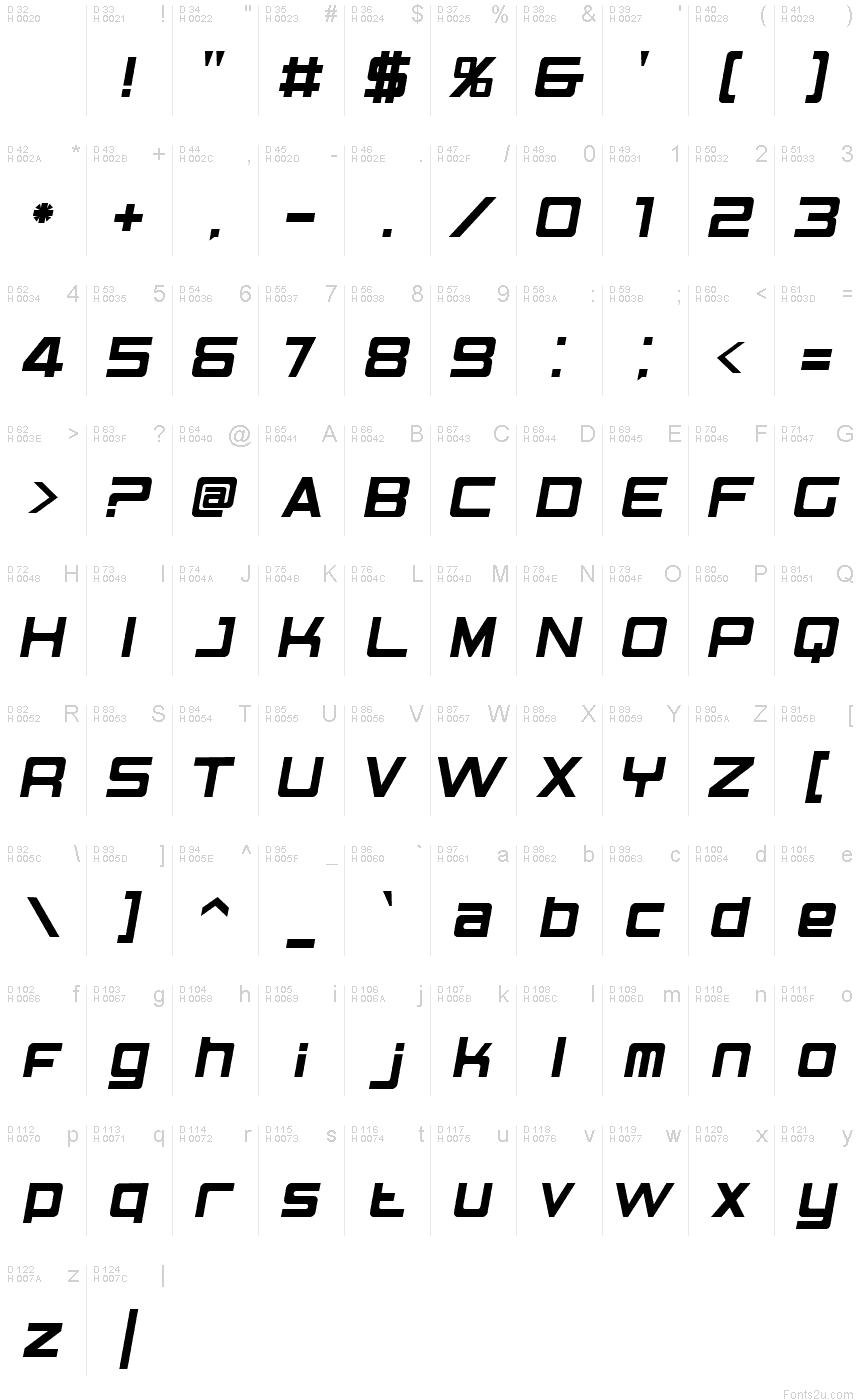
BN Elements od Bena Nathana to darmowy, nowoczesny krój pisma typu display, który przypomina zamrożony w kadrze ruch. Każda litera pochyla się do przodu, zachowując smukłą, pochyłą formę, ciasne odstępy i gładkie narożniki, co sugeruje prędkość bez agresywnego wyrazu. Rytm jest szybki i przejrzysty, nadając nagłówkom opływowy, aerodynamiczny charakter, który jest natychmiast czytelny, nawet z daleka lub na ruchomym nośniku.
Używając BN Elements, możesz nadać wysoką dynamikę brandingowi sportowemu, plakatom wyścigowym, zespołom e-sportowym, nakładkom do streamingu, grafice motoryzacyjnej czy odzieży technologicznej. Ten darmowy font sprawdza się wszędzie tam, gdzie liczy się szybkość, rywalizacja i nowoczesność. Połącz go z prostym geometrycznym bezszeryfowym krojem w przypadku tekstu głównego, a BN Elements niech gra pierwsze skrzypce w logotypach, wielkich tytułach i projektach bogatych w liczby.